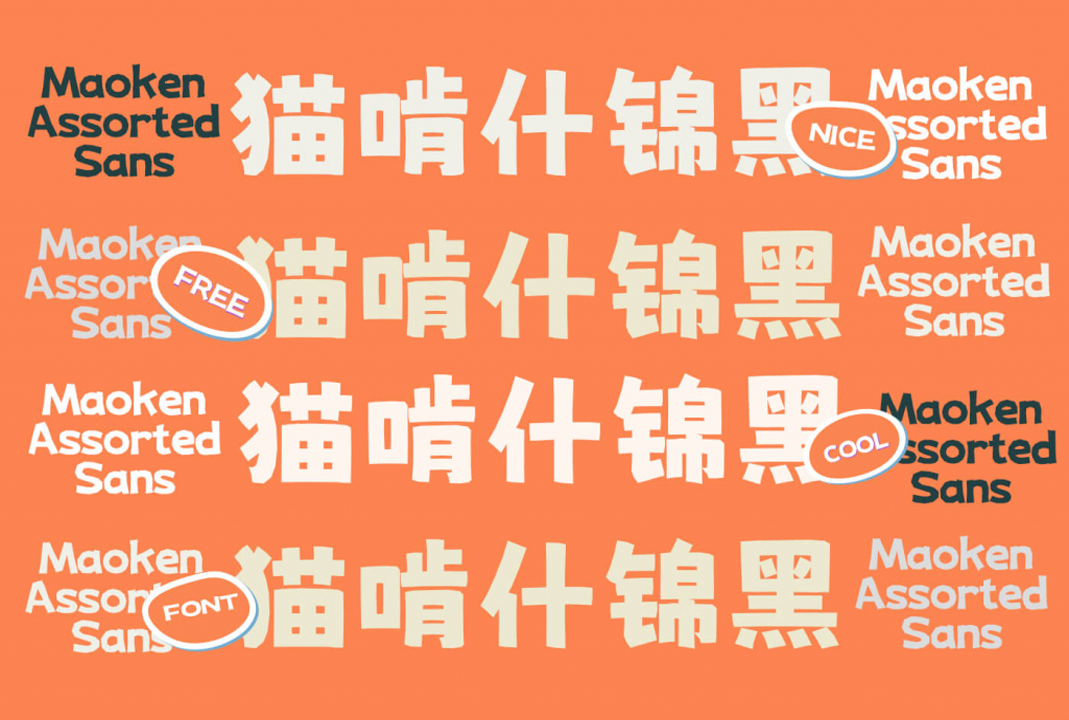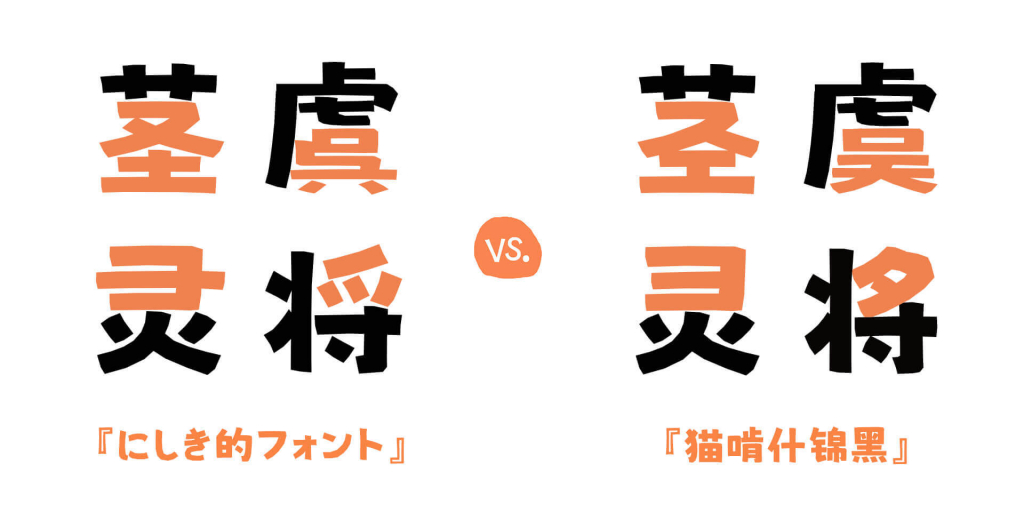
猫啃什锦黑(MaokenAssortedSans) | 免费商用中文字体下载
猫啃什锦黑是一款可爱的马克笔手绘风格中文免费商用字体,其笔画活泼有趣萌萌哒,特别适合做可爱类、母婴类等海报的标题字体。字体基于日本作者波間のかけひき创作的字体《にしき的フォント》(Nishiki-teki)进行简体字补充并对其中的汉字字形进行修改。